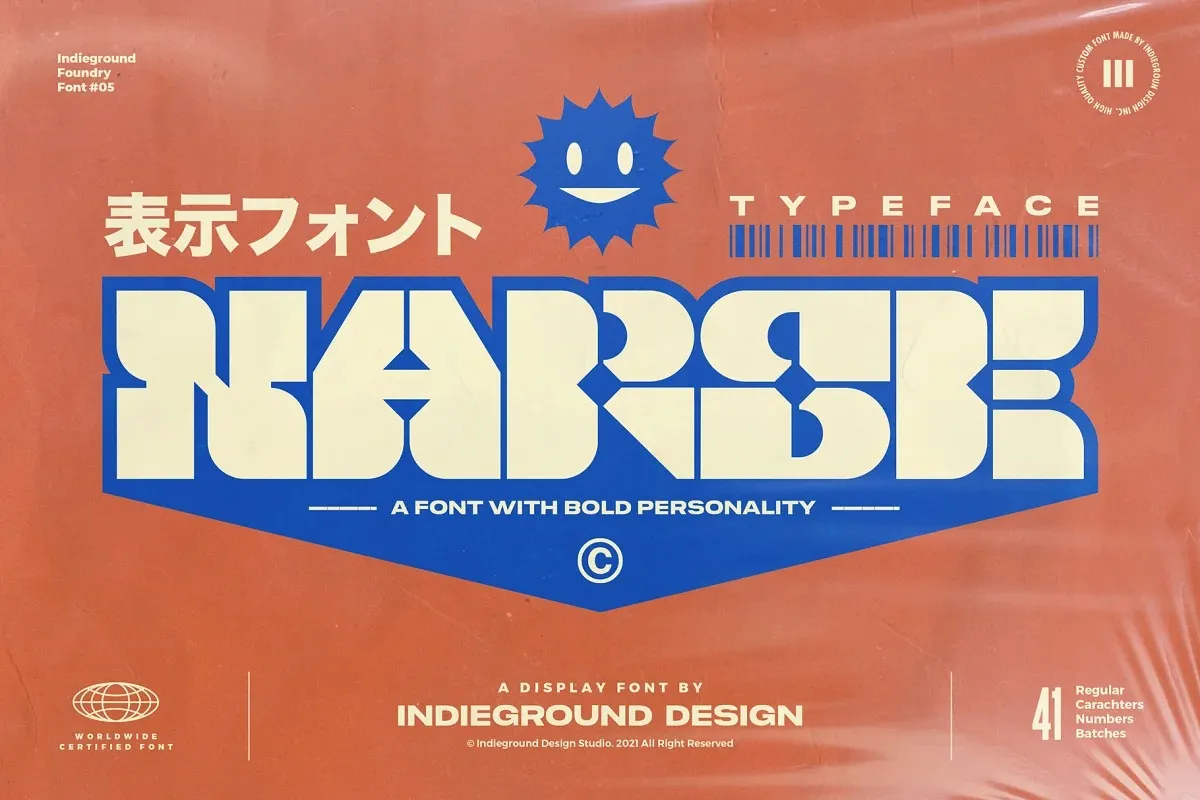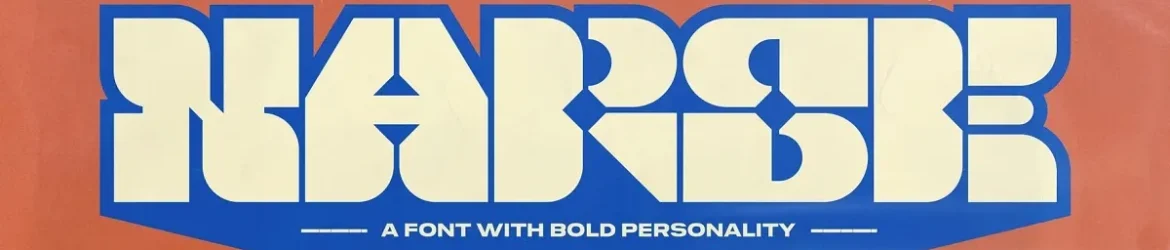
A Narse Font é uma opção perfeita para quem busca uma fonte display que se destaca e cria um impacto na sua arte digital ou impressa. Inspirada nas artes de capa de álbuns do jazz dos anos 70, mas com uma modernidade sólida e ousadia, esta fonte independente oferece uma perspectiva única no mercado das fuentes de exibição. Com alta contraste entre as letras e um desenho baseado em um módulo quadrado criado pela Indieground Team, a Narse Font traz uma atmosfera clássica ao mesmo tempo que adquirem um aspecto moderno e ousado. Esta versão comercial completa da Narse Font inclui todo o conjunto de caracteres, permitindo-lhe explorar as várias maneiras em que esta fonte pode moldar seus projetos artísticos. Seja para textos longos ou headlines chamativas, a Narse Font é uma escolha inteligente para designers e criativos que desejam adicionar um toque único e vibrante à sua obra. Perfecta tanto para aplicar em logotipos, como para título de capa, ou para qualquer elemento da arte digital que possa se beneficiar do seu design inovador e estilo marcante.